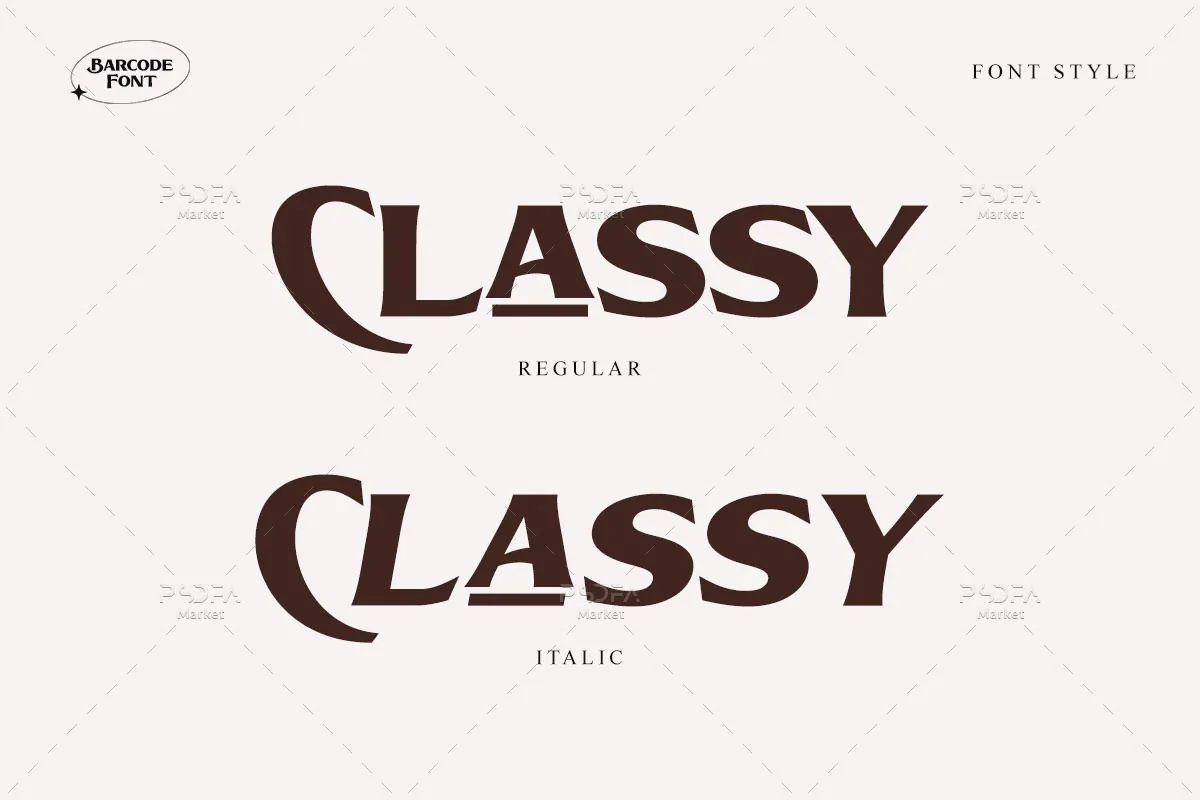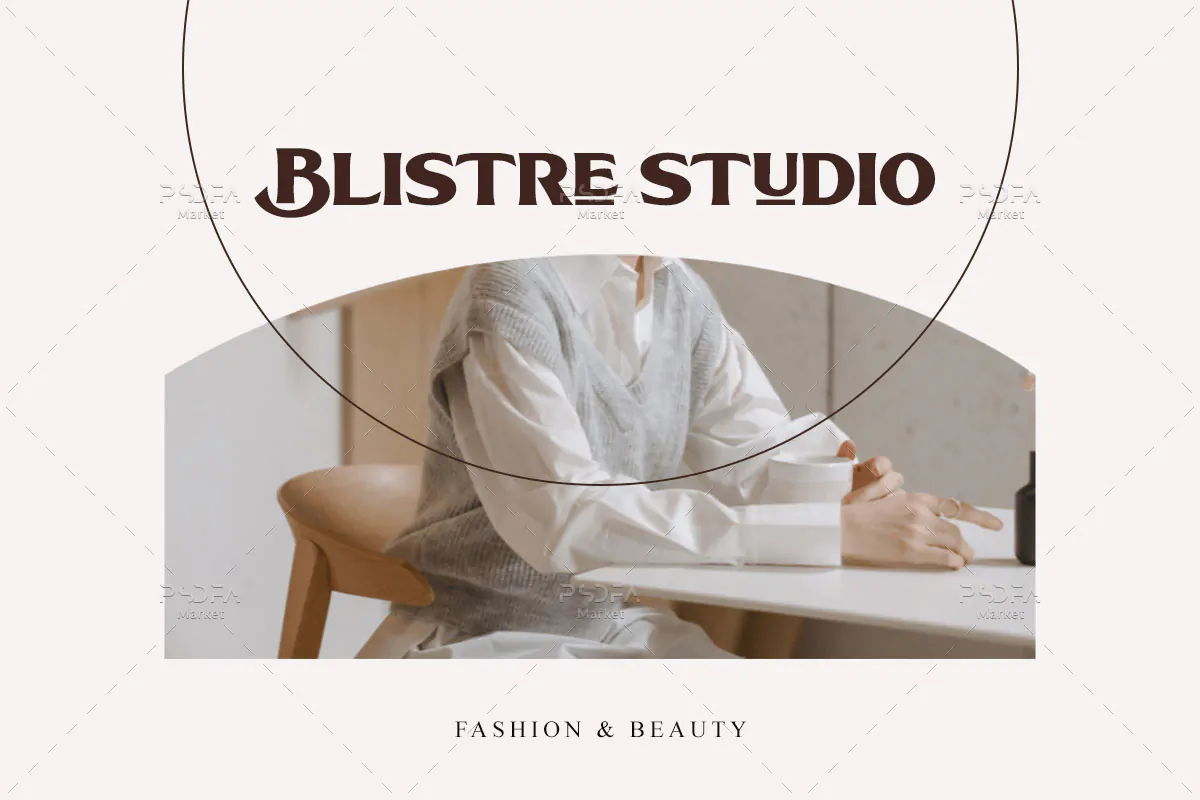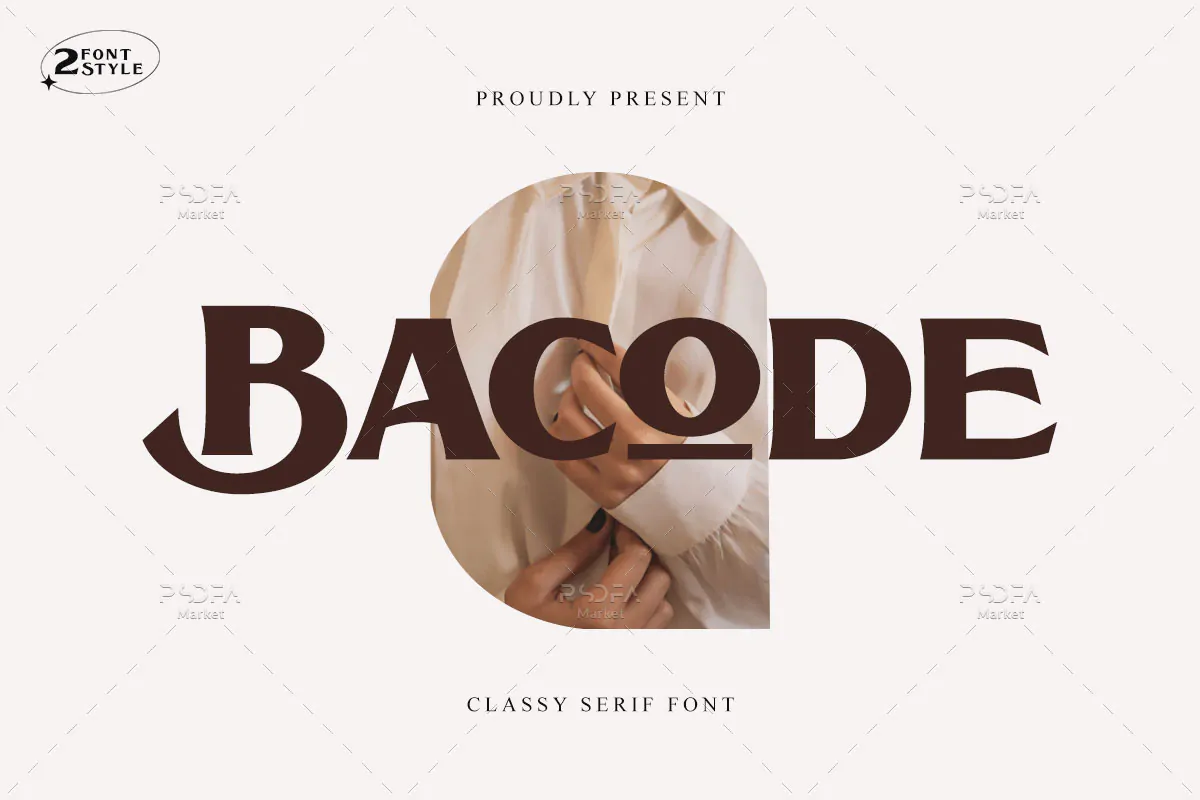
فونت کلاسیک Bacode
فونت کلاسیک انگلیسی
فونت کلاسیک Bacode یک قلم نمایشی انگلیسی است که مناسب برای استفاده در طرح و پروژههای گرافیکی مختلف میباشد. فونت Bacode با وزن معمولی طراحی شده است که میتوانید از آن در طراحی انواع پوستر، کارت ویزیت، بروشور، تراکت، بسته بندی محصولات و … استفاده کنید.